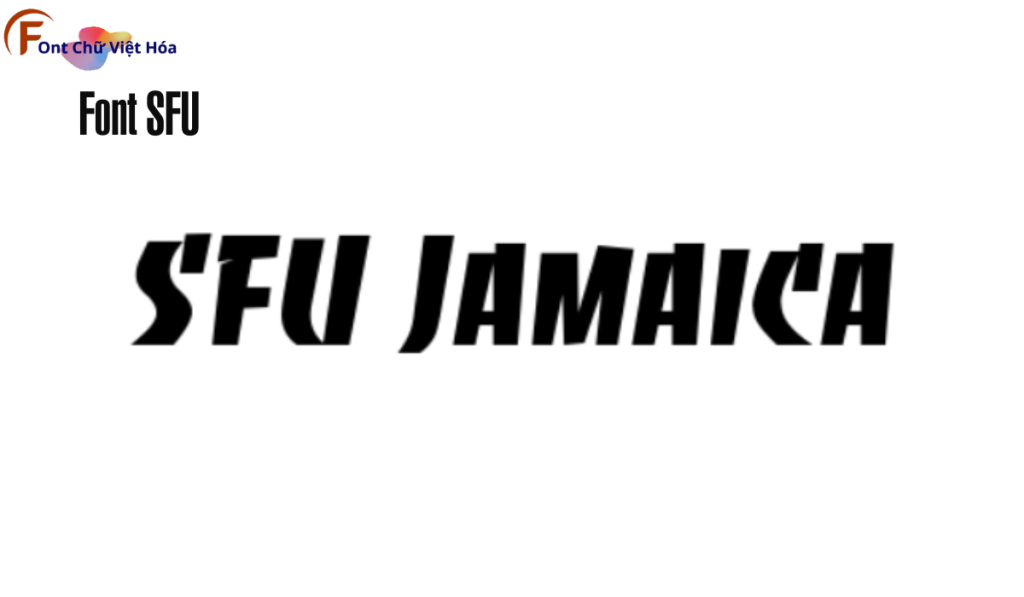
Font SFU Jamaica Việt Hóa
Kiểu chữ: Chữ không chân
Font SFU Jamaica Việt Hóa, thuộc bộ font SFU, mang đến hơi thở của sự tươi mới và năng động với phong cách sans-serif hiện đại. Font này được thiết kế nhằm mục tiêu tạo ra sự rõ ràng và dễ đọc, đặc biệt phù hợp cho các thiết kế sáng tạo như poster, logo, và tiêu đề. Đặc điểm hình dạng của SFU Jamaica là các đường nét đậm và tỷ lệ chữ cân đối, giúp tối ưu hóa không gian và tạo ấn tượng mạnh mẽ. Font này cũng đã được Việt hóa, mang đến sự linh hoạt và tiện dụng cho các dự án thiết kế bằng tiếng Việt, giúp người dùng dễ dàng tiếp cận và sử dụng.